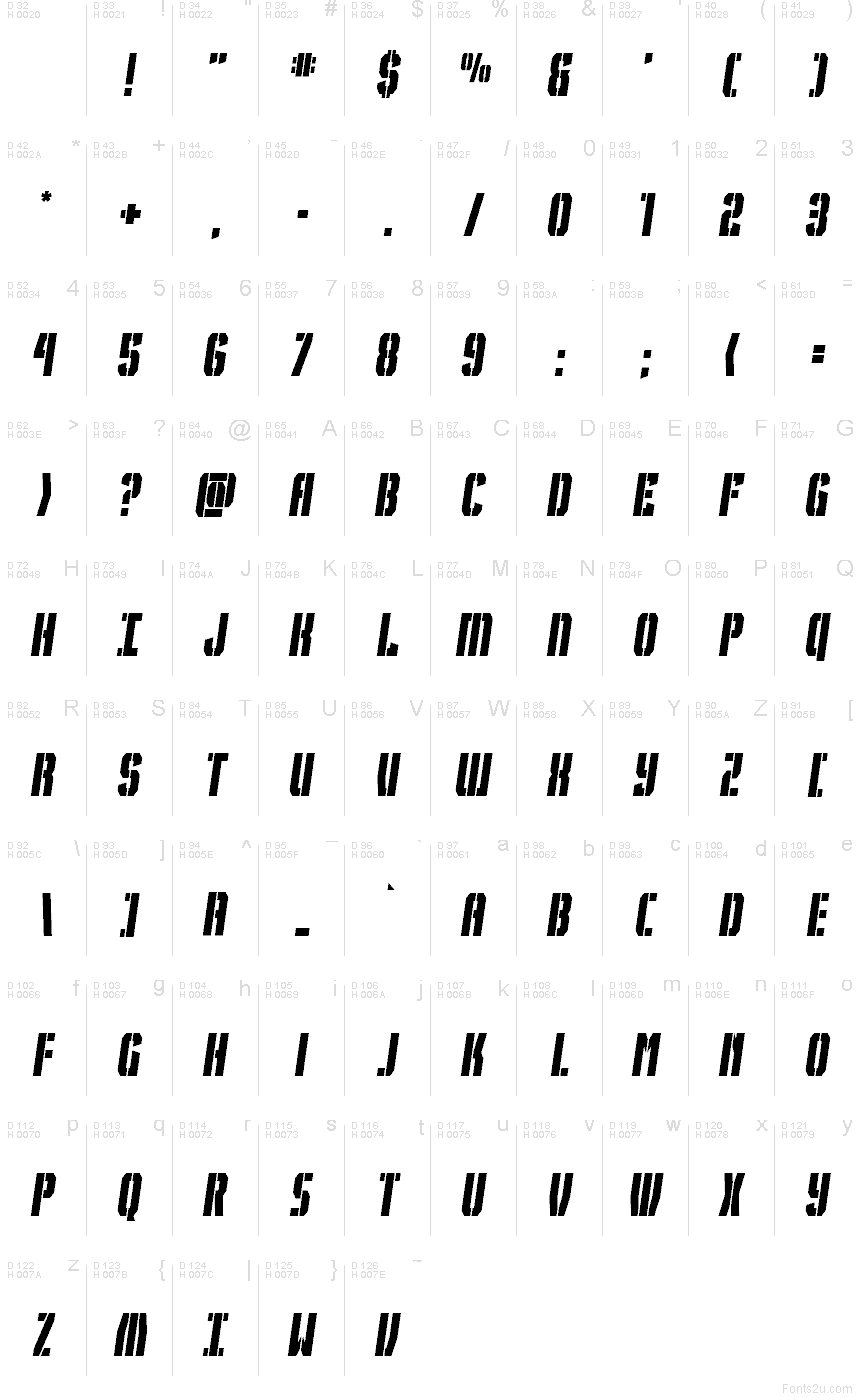
Gorilla Warfare, de Iconian Fonts, es una tipografía display gratuita de estilo militar con mayúsculas altas, cortadas en ángulos rígidos y dinámicos. Las letras transmiten fuerza y precisión; con sus siluetas en bloque, cortes internos ajustados y una ligera inclinación, todo el diseño evoca un ritmo marcial perfecto para carteles.
Esta fuente gratuita encaja a la perfección en logotipos de videojuegos, títulos de películas de acción, identidad de equipos, pósteres de eventos y titulares donde se necesite un ambiente táctico y combativo que refuerce el mensaje. También funciona de maravilla para títulos cortos y monogramas, ya que las mayúsculas se encajan de forma contundente y compacta, manteniendo una estética agresiva incluso en palabras cortas.
Gorilla Warfare Spaced Semi-It